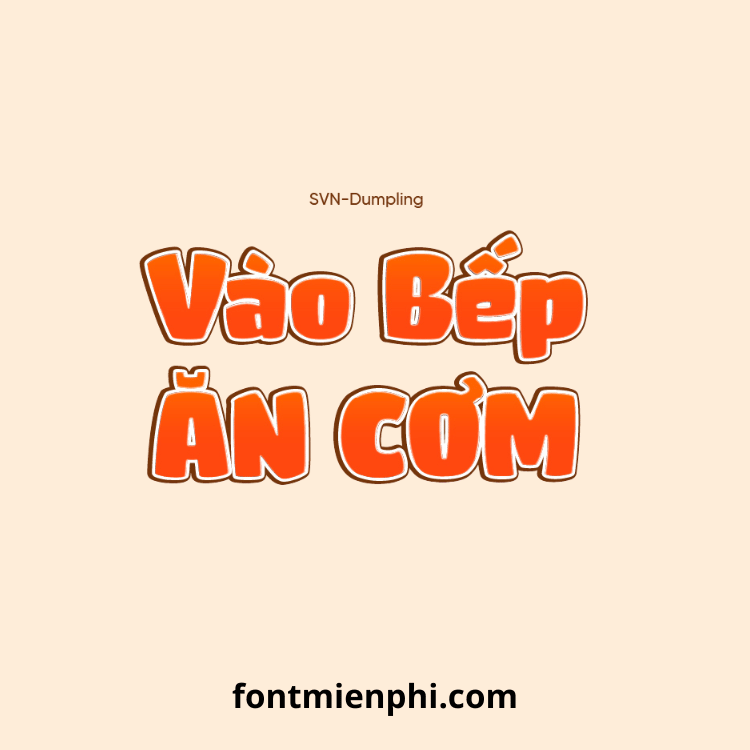
Font Việt Hóa SVN Dumpling – Nét Chữ Tròn Trĩnh Đáng Yêu Tựa Bánh Bao
SVN Dumpling là font chữ display việt hóa với hình dáng tròn trịa đáng yêu như những chiếc bánh bao xinh xắn. Với thiết kế độc đáo này, font chữ trở thành lựa chọn hoàn hảo cho các dự án thiết kế cần sự vui tươi và gần gũi.
Ưu điểm vượt trội:
Kiểu chữ tròn mềm mại – đường nét bo tròn đều tạo cảm giác thân thiện
Hỗ trợ đầy đủ tiếng Việt – bảo đảm tính thẩm mỹ khi sử dụng dấu
️ 2 phiên bản – Regular và Outline linh hoạt cho nhiều phong cách thiết kế
Dễ dàng phối màu – tương thích với các hiệu ứng gradient và layer style
Ứng dụng sáng tạo:
- Thiết kế bao bì thực phẩm, đồ ăn vặt
- Poster quảng cáo ẩm thực, sự kiện ẩm thực
- Thiết kế nhận diện thương hiệu quán ăn
- Ấn phẩm truyền thông cho đối tượng trẻ em
SVN Dumpling – Thổi hồn ẩm thực vào từng thiết kế với nét chữ tròn trĩnh như những chiếc bánh bao hấp dẫn!
- Font phù hợp nhất cho các tiêu đề ngắn
- Khuyến nghị sử dụng kích thước chữ lớn để thể hiện rõ nét đặc trưng
- Có thể kết hợp với các hình minh họa ẩm thực để tăng hiệu ứng